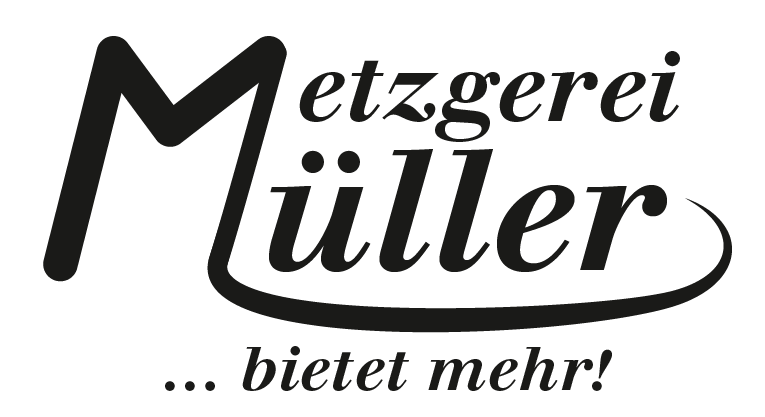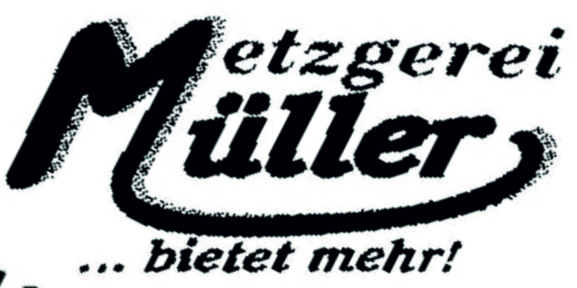
Suche Schrift dieser Metzgerei-Anzeige
für unseren Verein, der dieses Jahr ein Jubiläum feiert, haben verschiedene Sponsoren ihr Logo uns für den Druck in unserer Vereinschronik zugeschickt. Leider genügt die Qualität des hier gezeigten Schriftzuges nicht, um die gebuchte Anzeigengröße "auszufüllen". Leider gibt es auch keine andere Möglichkeit "das Original" einzuscannen/abzufotografieren  und an die Druckdaten kommt der Selbständige wohl nicht und ich wollte dann auch nicht x-mal nachbohren. Er meinte nun ich könnte das Logo einfach selbst Nachbilden. So viel zur Background Story :-)
Ich suche nun also die gleiche oder ähnliche Schriftart wie abgebildet. Darf in diesem Fall jedoch nichts kosten. Ob ich dann den Schattenwurf und diesen Schweif genau so hinbekomme, mal abwarten ;-)
Eingescannt wurde das Bild übrigens aus einer älteren Sponsoring-Anzeige. Gemacht wurde das Logo vor ca. 15 Jahren. Könnte mir jemand sagen, ob alle 3 Zeilen die gleiche Schriftart sind (außer Größe und Bold natürlich)
Sieht mir nach drei unterschiedlichen Schriftarten aus. Aus welchem Ort ist denn die Metzgerei?
auch wenn mich die Typografen hier jetzt steinigen wollen - ein halbwegs ähnlicher Font tuts auch... Achte auf das kleine g und i -das M von irgendeiner Rounded und alles - incl. Schweif im Illustrator zusammenbasteln.
Metzgereien haben ihr Logo doch auch immer auf Papiertüten etc. gedruckt. Vielleicht kannst du es von da scannen?
Leider  nur auf  Wurstdosen und auf einem Außenschild. Ich werde mein Glück nochmal damit versuchen.
Ok wieder was  dazu gelernt. Bin davon ausgegangen, dass diese feinen Serifen durch den Fettdruck verloren gegangen sind und es deswegen die ursprünglich gleich Schriftart war.
Danke, ja so hab ich das nun vor. Ich reihe mich zur Steinigung ein und geb zu, dass ich bisher nur unter den Windows Standard Schriftarten gesucht habe und ich dort keine gefunden haben mit eben diesem g und i. Ich werde bestimmt noch eine finden, hätte ja sein können, dass jemand ohne große Mühe sagt: "Ja klar, nimm diese "..."-Font.
Zumal das M insgesamt gezeichnet sein wird, diese von abnehmende Strichstärke lässt darauf schließen.
Und der Schatten: Schwanz-m erst mal zeichnen, grau färben, kopieren, und noch mal drüber legen, etwas nach links schieben und schwarz färben.
Warum muss das Logo überhaupt nachgebaut werden? Was spricht dagegen, Metzgerei Müller einfach in der Schrift zu schreiben, in der »Wir danken diesen Sponsoren für die freundliche Unterstützung« gesetzt wird? Die einfache Regel: wer ein druckbares Logo liefert, bekommt das; alles anderen bekommen ihren Namen.
Das Logo jetzt nachzubauen, würde dich doch etliche Stunden kosten und somit wenigstens ein paar hundert Euro wert sein. (Denn auch wenn du kein Geld verlangst, ist deine Zeit nicht wertlos! Selbst wenn du sie deinem Verein spenden möchtest, könntest du in der Logobauzeit eben Vereinsarbeit machen.) Der vom Metzger gespendete Betrag steht doch sicher in keinem Verhältnis dazu, oder?
Bleibt immer noch die Frage offen nach dem "woher stammt das?" Oft findet man auf den seltsamsten Wegen noch was, vorausgesetzt, man kennt den Ursprung …
Metzgerei Jürgen Müller aus Schapbach. Man wird jedoch nichts finden (auch nicht auf seiner Facebook-Seite).
Es spricht nichts dagegen, hab ja nur gefragt, ob mir jemand die Font oder eine ähnliche Font nennen könnte, da meines Erachtens dann eben der Wiedererkennungswert eben höher ist, selbst wenn es nur ein einfacher Schriftzug wird.
Nachdem die Metzgerei das Logo auch in jener Form verwendet:
würde ich das in beispielsweise einer Walbaum neu machen.
Schnell hingezimmert: